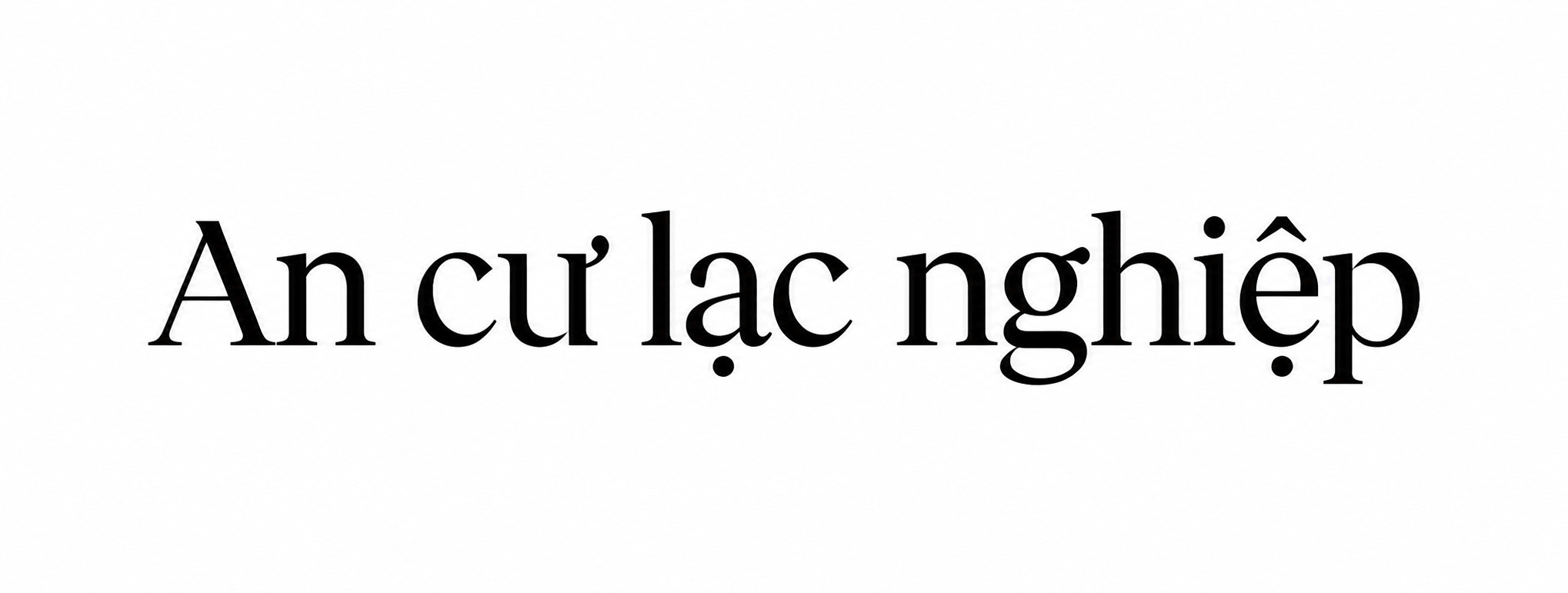
Nhiều designer tìm TAN Aegean Font Việt hóa thường gặp lỗi thiếu dấu tiếng Việt hoặc các đường nét uốn lượn bị đứt gãy khi phóng lớn để in ép kim trên hộp quà cao cấp. Những lỗi kỹ thuật này khiến thiết kế mất đi vẻ mềm mại, quý phái vốn có, đồng thời làm giảm sự chỉn chu của bao bì và hình ảnh thương hiệu trong mắt khách hàng VIP.
Font TAN Aegean là gì?
TAN Aegean là một bộ phông chữ thuộc dòng Display Serif đương đại được phát triển bởi xưởng đúc chữ TAN Type Co danh tiếng. Lấy cảm hứng từ vẻ đẹp phóng khoáng, ngập tràn ánh nắng của vùng biển Địa Trung Hải, phông chữ kết hợp hài hòa giữa cấu trúc chữ có chân cổ điển và những đường cong uốn lượn mang hơi thở nghệ thuật những năm 70. Nét đặc trưng của bộ chữ là độ tương phản sắc nét giữa các nét thanh mảnh mai và nét đậm đẫy đà, đi cùng các chi tiết cách điệu độc đáo ở các ký tự vòm, tạo nên một phong cách thời trang, kiêu kỳ và đậm tính thẩm mỹ biên tập.
Trong xu hướng thiết kế thương hiệu hiện nay, các ấn phẩm từ Bộ font TAN type Việt hóa nói chung và TAN Aegean nói riêng thường được các nhãn hàng nước hoa, mỹ phẩm hữu cơ, thời trang nghỉ dưỡng và đồ uống cao cấp lựa chọn làm điểm nhấn thị giác. Tuy nhiên, các đường uốn lượn phức tạp của bản gốc quốc tế thường bị xung đột khi kết hợp với hệ thống dấu thanh tiếng Việt. Bản Font việt hóa tan do In Viva chọn lọc đã được căn chỉnh tỉ lệ các dấu mũ, dấu móc theo chuẩn Unicode, hỗ trợ nhà thiết kế dàn trang mượt mà mà không làm mất đi tính cân xứng tự nhiên của con chữ.
Font TAN Aegean đẹp 01
Ký tự đã được rã vector chỉn chu, giữ nguyên tính hình học sắc nét khi in Offset khổ lớn hoặc làm khuôn bế.
5 ứng dụng TAN Aegean Font Việt hóa trong thiết kế và in ấn
Nhờ phong cách chữ mềm mại, quý phái cùng những đường nét mang cảm hứng nghệ thuật Địa Trung Hải, TAN Aegean Font Việt hóa được ứng dụng linh hoạt trên nhiều sản phẩm bao bì và quà tặng doanh nghiệp cao cấp:
• Thiết kế bao bì hộp mỹ phẩm và nước hoa cao cấp: Font TAN Aegean phù hợp để thể hiện tên thương hiệu, tên bộ sưu tập trên hộp giấy Ivory, hộp carton lạnh hoặc hộp cứng bọc giấy mỹ thuật. Những đường nét thanh thoát giúp sản phẩm tạo cảm giác tinh tế, phù hợp với các dòng mỹ phẩm hướng đến phân khúc sang trọng.
• Sản xuất bao bì hộp quà yến sào và trà cao cấp: Khi kết hợp cùng kỹ thuật ép kim, dập nổi trên nền giấy mỹ thuật hoặc carton lạnh, Font TAN Aegean giúp logo và tên sản phẩm trở nên nổi bật, tạo vẻ ngoài thanh lịch cho các bộ quà tặng tri ân khách hàng, đối tác VIP.
• In ấn thiệp mời sự kiện và thiệp cưới cao cấp: Với kiểu chữ giàu tính nghệ thuật, TAN Aegean phù hợp để trình bày tên nhân vật, tiêu đề chương trình hoặc thông điệp chúc mừng. Font chữ giúp các mẫu thiệp cưới, gala dinner hoặc thư cảm ơn mang nét lãng mạn, tinh tế hơn.
• Gia công nhãn chai rượu vang và sản phẩm phong cách sống: Font TAN Aegean có thể ứng dụng trên nhãn chai rượu, nến thơm, hộp quà thủ công khi kết hợp cùng giấy mỹ thuật có vân hoặc kỹ thuật ép kim. Thiết kế tạo cảm giác cổ điển, sang trọng và có chiều sâu.
• Trang trí túi giấy thời trang và bộ nhận diện thương hiệu: Logo sử dụng Font TAN Aegean trên túi giấy Kraft trắng, Ivory hoặc giấy mỹ thuật giúp các thương hiệu thời trang, phụ kiện xây dựng hình ảnh thanh lịch, cao cấp và dễ tạo dấu ấn với khách hàng.
Font TAN Aegean đẹp 02
Để thành phẩm in ấn ứng dụng TAN Aegean Font Việt hóa đạt độ sắc nét và giữ được vẻ đẹp nghệ thuật, designer cần chú ý các yếu tố kỹ thuật sau:
• Kiểm soát độ mảnh của nét chữ khi in: TAN Aegean có nhiều chi tiết uốn lượn và nét thanh mảnh. Khi sử dụng trên bao bì kích thước nhỏ hoặc chất liệu giấy mỹ thuật có bề mặt nhám, cần kiểm tra kích thước chữ để hạn chế tình trạng mất nét.